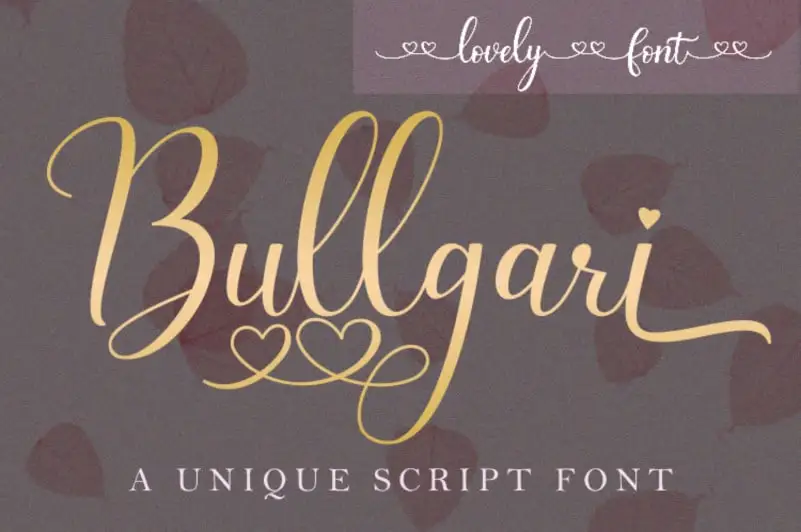
A Bullgari Calligraphy Font é uma elegante tipografia script que transmite um ar contemporâneo junto com uma formação perfeita inspirada na clássica caligrafia de época. Com sua assinatura fina e atraente, mas não excessivamente grossa, essa fonte traz equilíbrio e diversidade ao seu design. Ideal para aprimorar o encanto de seus projetos gráficos, Bullgari Calligraphy Font proporciona um toque único que complementará sua visão criativa. Ideal para designers que valorizam tanto a sofisticação quanto a modernidade, essa fonte é perfeita para criações com uma pegada clássica mas atual. Ela está disponível para aqueles que procuram adicionar algum encanto ao design de materiais publicitários, gráficos digitais ou até mesmo aos documentos profissionais. Com Bullgari Calligraphy Font na sua biblioteca, você poderá explorar um novo nível de expressão visual e tornar seus projetos ainda mais memoráveis.